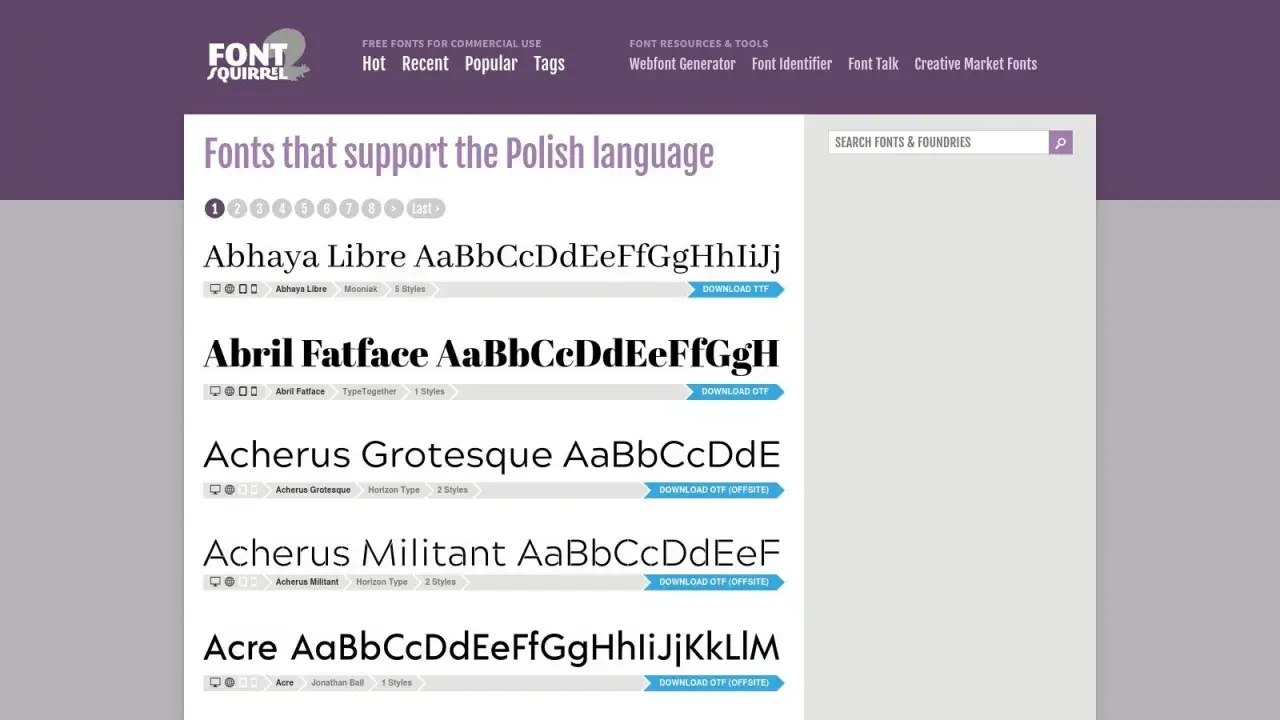
Polskie litery nie są dodatkiem do tekstu, tylko częścią jego czytelności, rytmu i wiarygodności. Gdy projektuję treść na stronę, patrzę nie tylko na to, jak wyglądają wszystkie polskie znaki, ale też czy font radzi sobie z nimi w nagłówkach, akapitach i na mobile. W tym tekście pokazuję konkretną listę tych liter, wyjaśniam ich typograficzne cechy i podpowiadam, jak sprawdzić, czy czcionka naprawdę wspiera polski alfabet.
Najważniejsze rzeczy o polskich literach i fontach, które warto sprawdzić przed publikacją
- W polszczyźnie jest 9 liter diakrytycznych: ą, ć, ę, ł, ń, ó, ś, ź i ż.
- W typografii liczy się nie tylko obecność znaków, ale też jakość ich kształtu, proporcji i odstępów.
- Na stronie kluczowe są UTF-8, pełne pokrycie glifów i sensowny zestaw fallbacków.
- Najczęstsze problemy to brak polskich liter w fontach, zła obsługa bold/italic i tekst zamieniony na obraz.
- Dobrze dobrana czcionka musi działać zarówno w treści, jak i w menu, przyciskach oraz nagłówkach.
Jakie litery tworzą polski alfabet z diakrytykami
W polskim alfabecie litery z diakrytykami są pełnoprawnymi znakami, a nie ozdobą dodaną „na wszelki wypadek”. To ważne rozróżnienie, bo w praktyce wpływa na pisownię, sortowanie, wyszukiwanie i wygląd tekstu w fontach. Poniżej masz kompletny zestaw liter, które najczęściej pojawiają się w polskiej typografii.
| Litera | Rodzaj znaku | Co warto o niej wiedzieć |
|---|---|---|
| ą | ogonek | Samogłoska nosowa, często problematyczna w małych rozmiarach, jeśli font ma słabą dolną część glifu. |
| ć | kreska | Wymaga dobrego odstępu między kreską a główną bryłą litery. |
| ę | ogonek | Przy cienkich krojach ogonek łatwo traci czytelność. |
| ł | przekreślenie | Jedna z liter, po której szybko widać jakość fontu, bo nie każdy krój dobrze rozwiązuje ukośną kreskę. |
| ń | kreska | W wersji kapitalikowej bywa najłatwiej obciąć ją zbyt ciasnym interliniowaniem. |
| ó | kreska | Prosty znak, ale w słabych krojach kreska bywa zbyt cienka albo za krótka. |
| ś | kreska | W nagłówkach i przy większym rozmiarze łatwo zauważyć, czy kreska nie jest „doklejona”. |
| ź | kreska | Warto pilnować, by kreska była czytelna także w boldzie. |
| ż | kropka | To znak, który najczęściej zdradza niedopracowany font w wersji display. |
W praktyce patrzę na te litery jak na test jakości kroju pisma. Jeśli font dobrze radzi sobie z ą, ł i ż, zwykle znaczy to, że projektant przewidział polski tekst, a nie tylko łaciński szkielet alfabetu. Kiedy wiesz już, jakie litery wchodzą w grę, łatwiej ocenić, czy font naprawdę je obsługuje.
Dlaczego font musi mieć pełne pokrycie znaków
Tu zaczyna się różnica między samym kodowaniem a realnym wyglądem tekstu. Kodowanie mówi komputerowi, jaki to znak, a glif jest jego graficzną postacią. Możesz mieć poprawny tekst w UTF-8, a mimo to zobaczyć brzydki zamiennik, jeśli czcionka nie ma danego glifu albo ma go narysowanego byle jak.
W typografii webowej najważniejsze są trzy rzeczy. Po pierwsze, font musi zawierać polskie glify, najlepiej przynajmniej z zakresu Latin Extended-A. Po drugie, musi mieć sensowne odmiany regular, bold i italic, bo brak jednej z nich często kończy się sztucznym „dociążaniem” litery przez przeglądarkę. Po trzecie, powinien mieć poprawne fallbacki, czyli listę zapasowych fontów, które przejmą tekst tylko wtedy, gdy główny krój zawiedzie.
To ważne także przy sortowaniu i interfejsach. W polszczyźnie litery z ogonkiem i kreską mają własne miejsce w alfabecie, więc katalog produktów, lista autorów albo filtr w sklepie powinny uwzględniać lokalne zasady, a nie tylko angielski porządek A-Z. Właśnie ten rozdźwięk między poprawnym kodem a słabym glifem najczęściej wychodzi przy praktycznym teście.
Jak sprawdzić font w praktyce, zanim opublikujesz stronę
Na etapie testów nie wystarczy spojrzeć na jeden ładny nagłówek. Ja zawsze sprawdzam font na dłuższym tekście, w różnych wagach i na kilku urządzeniach, bo dopiero wtedy widać, czy diakrytyki są czytelne, czy tylko „jakoś się mieszczą”.
- Wstaw próbny tekst z każdą polską literą, najlepiej w wersji małymi i wielkimi literami.
- Sprawdź nagłówki, akapity, menu, przyciski i formularze, bo każdy z tych elementów ma inne proporcje.
- Otwórz stronę na telefonie i na desktopie, bo renderowanie czcionek różni się między systemami.
- Przetestuj regular, bold i italic, żeby zobaczyć, czy kreski i ogonki nie deformują się po zmianie grubości.
- Wyłącz na chwilę webfont i zobacz, jak wygląda fallback, jeśli główny font nie zdąży się załadować.
W takim teście dobrze działa też klasyczna fraza „Zażółć gęślą jaźń”, bo szybko pokazuje wszystkie polskie litery w jednym miejscu. Jeśli ta linia wygląda poprawnie, to zwykle jesteś już bardzo blisko bezpiecznej publikacji. Kiedy test przejdzie, zostaje jeszcze lista najczęstszych pułapek, które potrafią zepsuć efekt.
- Czy kapitaliki i wersaliki nie obcinają ogonków oraz kresek?
- Czy w widocznych treściach zachowujesz polskie znaki, zamiast usuwać je „dla bezpieczeństwa”?
- Czy techniczne wyjątki, takie jak slug w URL-u, są rozwiązywane osobno, a nie kosztem czytelności tekstu?
Jeśli font obsługuje wszystkie polskie znaki, dokument jest w UTF-8, a diakrytyki wyglądają dobrze w kilku rozmiarach i wagach, masz już solidną bazę. Reszta to dopracowanie proporcji, odstępów i charakteru kroju, czyli dokładnie ten etap, na którym dobra typografia zaczyna pracować na wiarygodność całej strony.